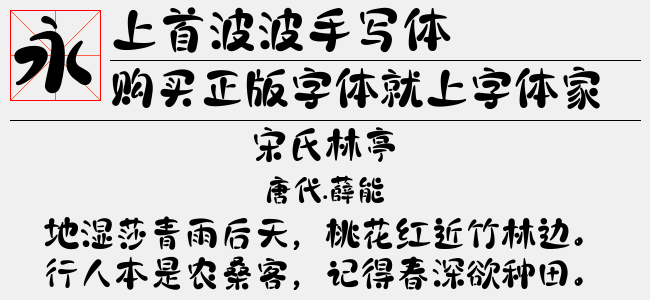
上首波波手写体
字体作者:上首造字
字体名称:上首波波手写体
字体家族:上首造字
书体类型:手写/印刷类
字体公司:上首造字
上首波波手写体
上首波波手写体,简体中文约6763字。本套字主要是以一端粗一端细的圆润的笔画和圆点书写,笔画整体浑圆,柔和、可爱,像果冻,像水滴,像中文感叹号,给人以温柔、俏皮、波动,胖乎乎、萌萌哒的感觉。本套字适用于搭配视频、书信、海报、专辑、商业广告等大众属性。